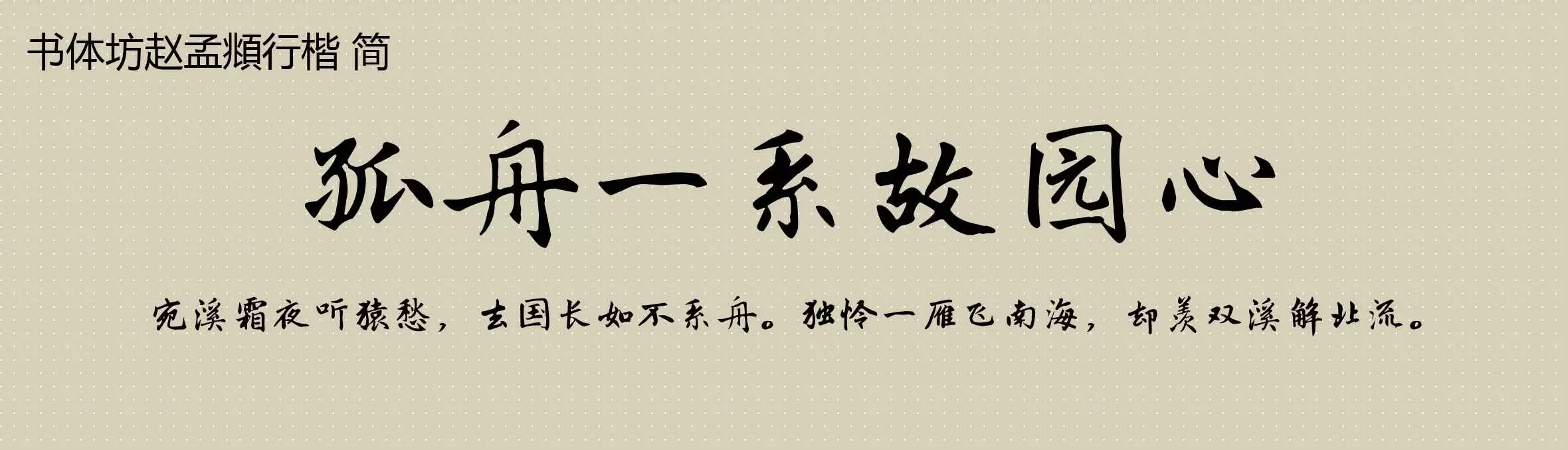
书体坊赵孟頫行楷简是一种精美的中文字体,其漂亮的书写风格源于中国书法大师赵孟頫所书写的行书,经过了现代设计的精心绘制和整理而成。这种字体的基本特征是线条简练流畅,笔画有力有度,整体感觉大气稳重,适合用来表现正式、庄重的文字内容,比如书信、名片、创意广告等。书体坊赵孟頫行楷简在当今的设计领域中,得到了广泛的应用和好评。